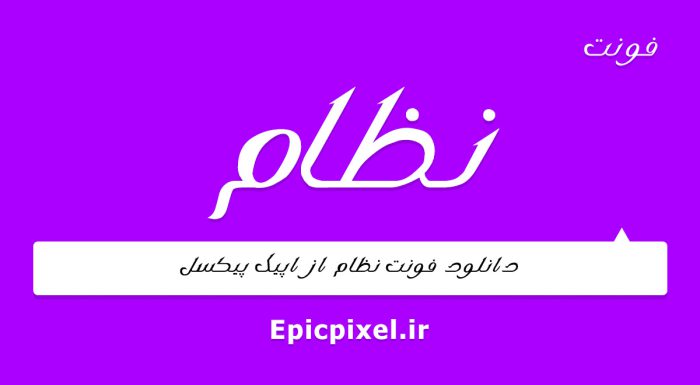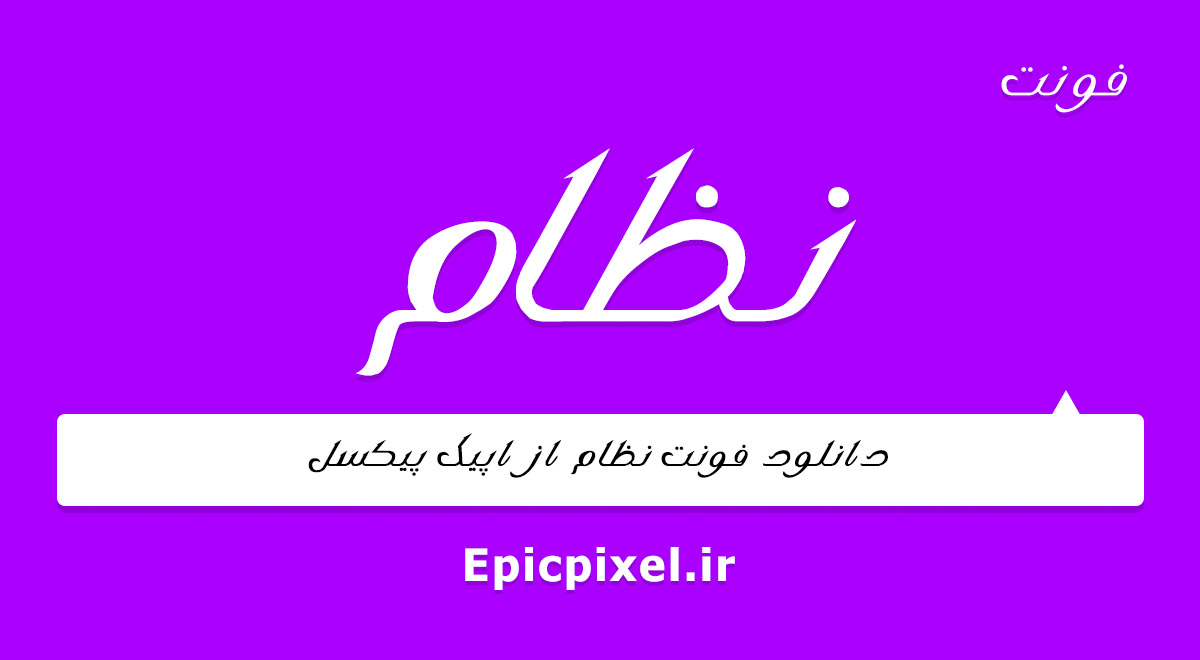
2 فونت نظام فارسی
فونت های فارسی نقش مهمی در زیبایی و خوانایی متون فارسی ایفا می کنند. فونت «نظام» به عنوان یک فونت فارسی، ویژگی های منحصربه فردی دارد که آن را برای استفاده های گوناگون مناسب می سازد. این فونت با طراحی ساده و خوانا، تجربه ی کاربری بهتری را در مطالعه و نگارش متون فارسی فراهم می کند.
یکی از ویژگی های برجسته ی فونت نظام، هماهنگی و انسجام حروف آن است. این ویژگی باعث می شود کلمات و جملات به صورت یکپارچه و روان دیده شوند و خواندن متن را آسان تر می کند. این فونت به دلیل طراحی دقیق، در اندازه های مختلف نیز خوانایی خود را حفظ می کند و برای استفاده در عناوین، متون اصلی و حتی متون ریز مناسب است. همچنین، فونت نظام از اعراب و نشانه های فارسی به خوبی پشتیبانی می کند و از این نظر مشکلی برای کاربران ایجاد نمی کند.
در کنار مزایا، باید به این نکته هم اشاره کرد که فونت نظام طراحی نسبتاً ساده ای دارد و شاید برای پروژه هایی که نیاز به فونت های بسیار خاص و فانتزی دارند، مناسب نباشد. با این حال، سادگی این فونت خود یک مزیت محسوب می شود، زیرا باعث می شود متن رسمی تر و جدی تر به نظر برسد. اگر به دنبال فونتی هستید که در عین خوانایی و زیبایی، سادگی و رسمیت را نیز به متن شما ببخشد، فونت نظام یک انتخاب عالی است. این فونت رایگان است و به راحتی می توانید آن را دانلود و در پروژه های خود استفاده کنید.